坚持手绘做字六十余年,只为赋予字体本该有的生命力
Hirano Kouga
平野甲賀の
赋予字体该有的生命力
字体必须像空气一样,可以放心地呼吸。
——平野甲賀
平野甲賀(Hirano Kouga)日本平面设计师、书籍设计师。1938年生于京城(现韩国首尔),毕业于武藏野美术学校(现武藏野美术大学)视觉设计科毕业。以独特的手绘文字设计约六千本书。主要著作包括《平野甲贺──书籍设计之书》(一九八五年,Libroport)、《平野甲贺「造书」术‧我喜欢的书形》(一九八六年,晶文社)、《文字的力量》(一九九四年,晶文社)、《描绘文字(文字を描く)》(二○○六年,SURE);CD-ROM出版品包括《文字的力量─平野甲贺的作品》(一九九五年,F2)、手绘文字字体「甲贺怪怪体」假名篇(二○○四年,BZBZ)与《甲贺怪怪体06》汉字篇等等。
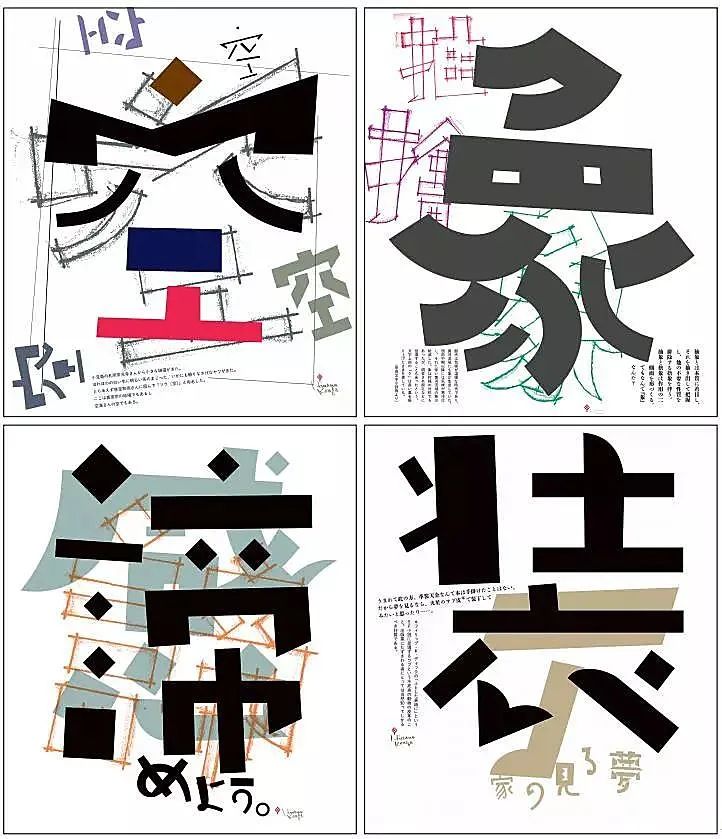
平野先生是日本设计界一位特殊的平面设计师,在他几十年的书籍装帧生涯里,将个人特色鲜明的手绘文字,应用到大量的书籍装帧中。他创作的手绘字虽然外观保持着朴素的形态,但却有着极高的识别度和艺术水准。
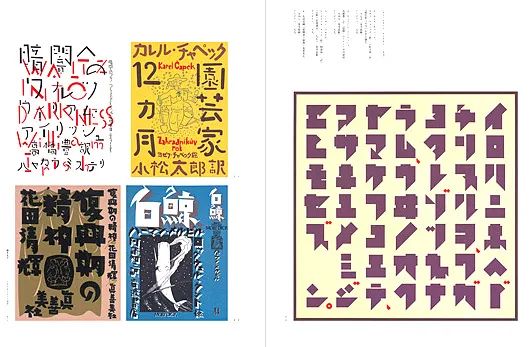
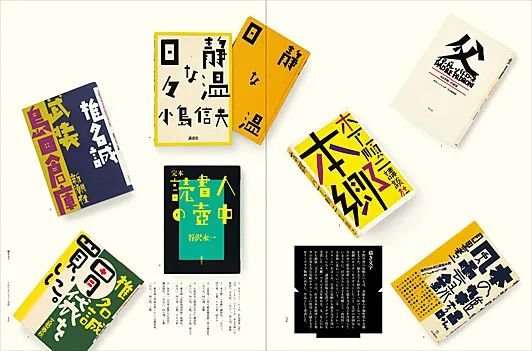
以独特的线条呈现朴素与趣味兼具的手绘文字,从60年代至今仍不断在书的世界中漫舞,以文学大师大江健三郎的小说《先跳再看》设计海报,获得当时非常重要的「日本美术宣传协会」展览特选奖。
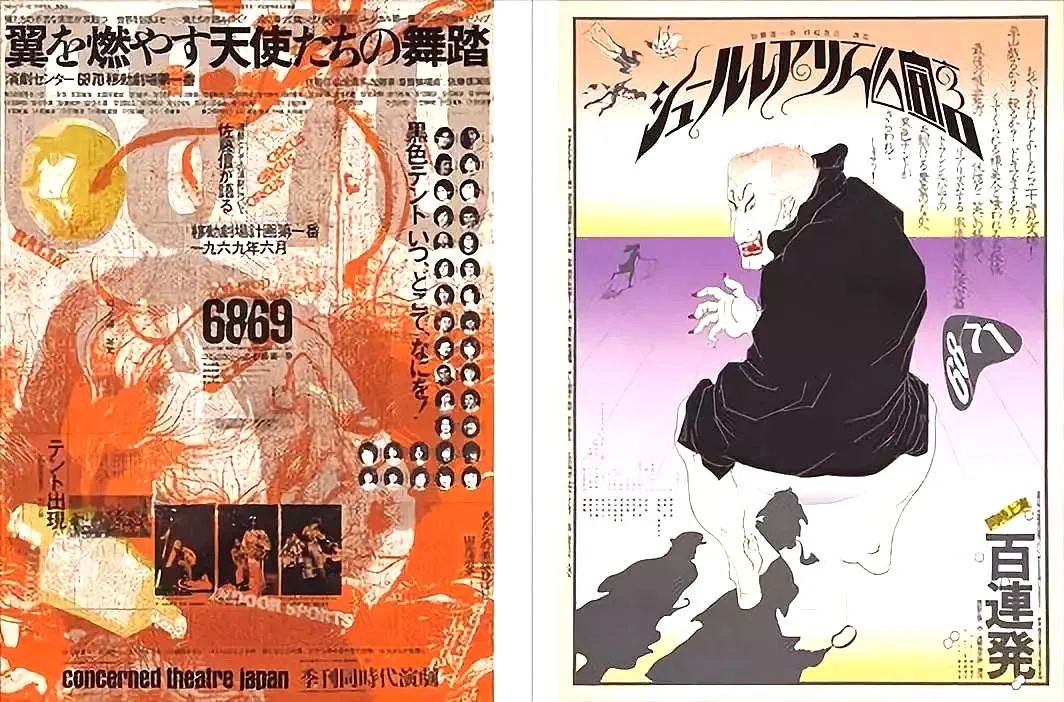
字体必须像空气一样
平野先生从1964至1991年,一手设计统筹晶文社所有书籍的封面及装订,为出版社建立了特有的企业形象。一九八三年为木下顺二《本乡》设计封面,荣获第十五届讲谈社出版文化奖书籍设计类大奖。平野先生以独特的手绘文字设计了高达六千多本书,而他的创作方式一直坚持着传统手绘的方式完成。
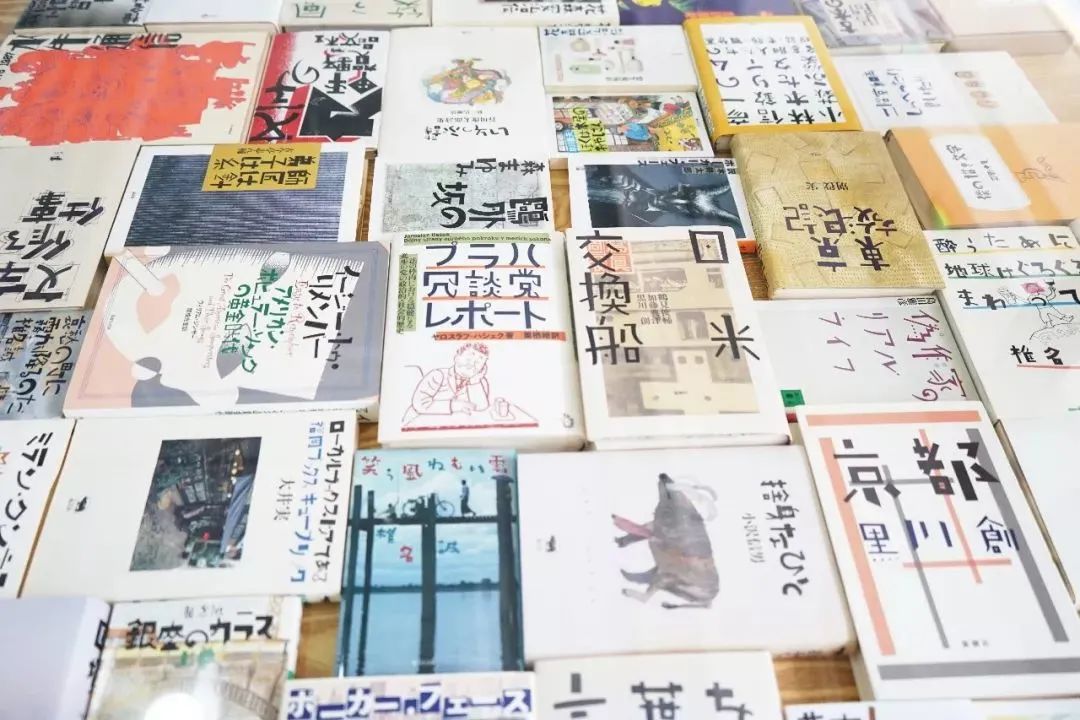
有人认为他受到俄罗斯形式主义的“斜型风”所影响,开发的字型风格独特,每个字体一亮相,如同漫画人物,手脚翩然起舞!
无人出其右,植草甚一、椎名诚、小野二郎、今江祥智、中平卓马、恩田陆等等名家的作品都由他操刀。同时也与「黑帐篷剧团」、「水牛乐团」交流匪浅,经手无数平面文宣、海报与剧场设计。二○○五年于东京神乐坂「theater iwato」小剧场担任艺术总监。
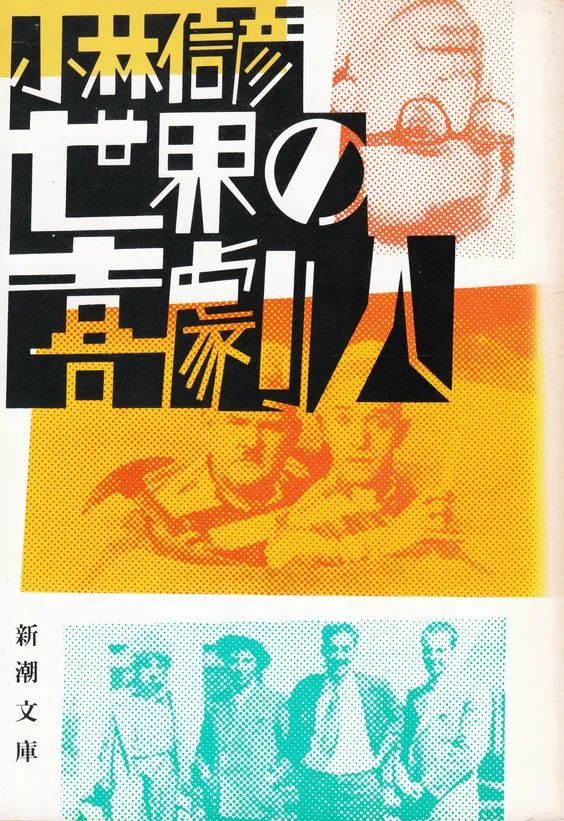
平野甲贺自己则认为:字体应该得像空气一样,可以放心地呼吸~
使用不适合的字体会引起类似花粉症的不适感,会让人打喷嚏。文字和书本间存在着一种气氛,有些字不能那么用,逐渐就体会到设计的微妙尺度。
将字体赋予特定的生命力
平野先生常说,每个字体都应该有它们特定的生命力,字体无需太过于工整,太过于工整反而失去了它原本的意义。如果无法确保掌控一个字的风景时,是写不出好的字体的~
比方说“父”这个字,自从由中国人发明以来,已被无数人使用,所以夸张一点说,当人们面对父这个字的时候,文字本身蕴含的历史与故事,也全面地向我逼近。而我是出自于独善其身的思考存在的,文字力不是由平野甲贺的“力文字“而生,而是出自本身那股远远超乎个人思想的力量……。
经过软件排版后,被修得工工整整的那些文字,已经成为任何人都可以安心使用的共通符号,得以稳定地存在于世界上。但是我有一股热情,想要知道文字本身更进一步的意义,所以就想要自己动手画。
比方说像「瓶」字,我脑子裡马上就会跑出有点锐利的感觉。单看瓶子或许很圆滑无害,而一旦破了,就顿时化成危险利器。
这可能跟书籍内容本身没有绝对关係,我从书中撷取灵感,再加上自己的感觉、将之扩大。
至于怎麽写出来的文字才叫文字,虽然我常常把文字写得快要脱离原本的形状,但我为了得到合乎自我审查的文字,不仅顺著文字本来的力量书写,也将那些使我存在的经验全部拿出来再利用,才能写出有力量的文字。这都是由我的意识让这些文字得以依照合适的型态诞生出来,而这也就是设计者工作的意义。
探索字体的更多可能
平野先生后来常说,自己非常逃避完美无缺,一旦至臻完美,就表示没戏唱了。“我想要写出更加朴拙的文字,并且导引各种改变这些字的可能”
我很喜欢不规则的字体。我自己写的文章很幼稚、孩子气,所以也喜欢使用这种像小孩般不规则的字感、天真无邪;像书中的明体看起来煞有介事,很严肃,感觉该写在捲轴上呢。
这种字形很有意思。日本在儿童乐园、急诊室、医院,还有电车的标示等,用的多半是都是,好比在不断强调“这里是安全无害的”。这些根源于儿时的经验让人自然而然有了既定印象,想用这个字体告诉读者:「没有什麽艰涩内容喔~这里一点也不危险喔~」
在可怕的内容上运用这种字体,仿佛可以抑制那种可怕的感觉。身为设计师,能做的也只有这样,忠实呼应自己的儿时体验。
到现在为止,我还一直思考着手绘对文字更多可能性的探索。所以这也是我一直使用纯手绘做字的初心。软件做出来的文字与用真笔画出来的文字还是存在一定的区别性的。手绘可以根据适合当下的温情进行疏解,而软件做出来的我认为还缺少了字体本应该有的生命力。